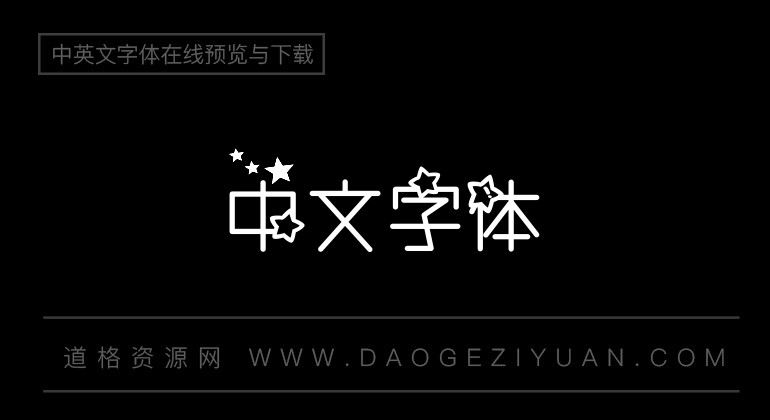
阿西-你好星期四是一款由荷兰设计师Astrid Stavro创作的字体,它具有古典的外观,圆润的线条,简洁的字形,清晰的细节,以及精致的字体结构,有助于提高文本的可读性。它可以用于多种语言,包括英语,西班牙语,德语,法语,意大利语,葡萄牙语,荷兰语等。此外,它还可以用于商业广告,书籍,海报,网站,报纸,杂志等多种媒体。文件名:AXi-NiHaoXingQiSi-2.ttf
阿西-你好星期四是一款非常不错的手写艺术字体,具有很好的视觉感,适合于文化类的宣传设计、商业类品牌的广告和产品包装设计以及个性化文字排版等较多场景。